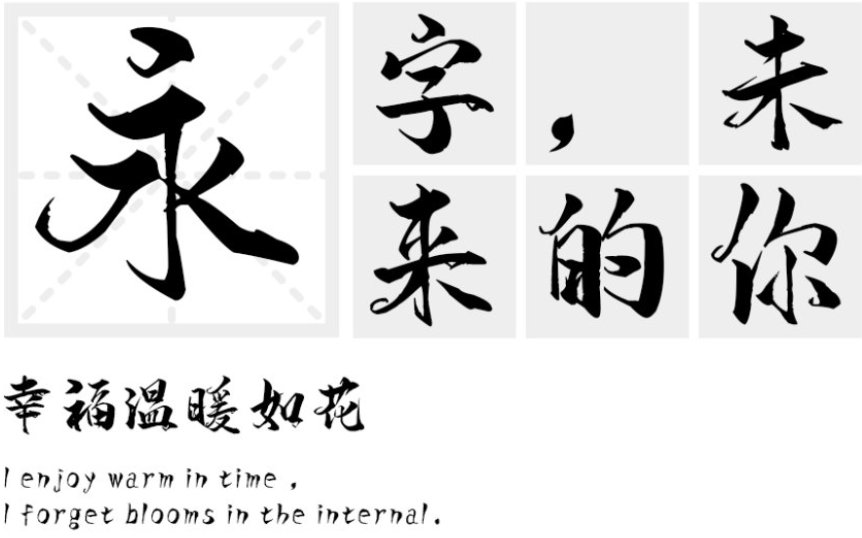
汉标智造国楷发布
字体名称:汉标智造国楷
字体类别: 书法字体
适用场景:LOGO、广告、屏显、影视
汉标智造国楷简介:汉标智造国楷字体是一款适合手写艺术和广告设计的字体,书法气息浓厚,结字潇洒俊逸,运笔行云流水,气韵生动。适用于文艺类的书刊、品牌广告和产品包装设计,以及社交网络的个性化用字。
汉标智造国楷预览图展示: